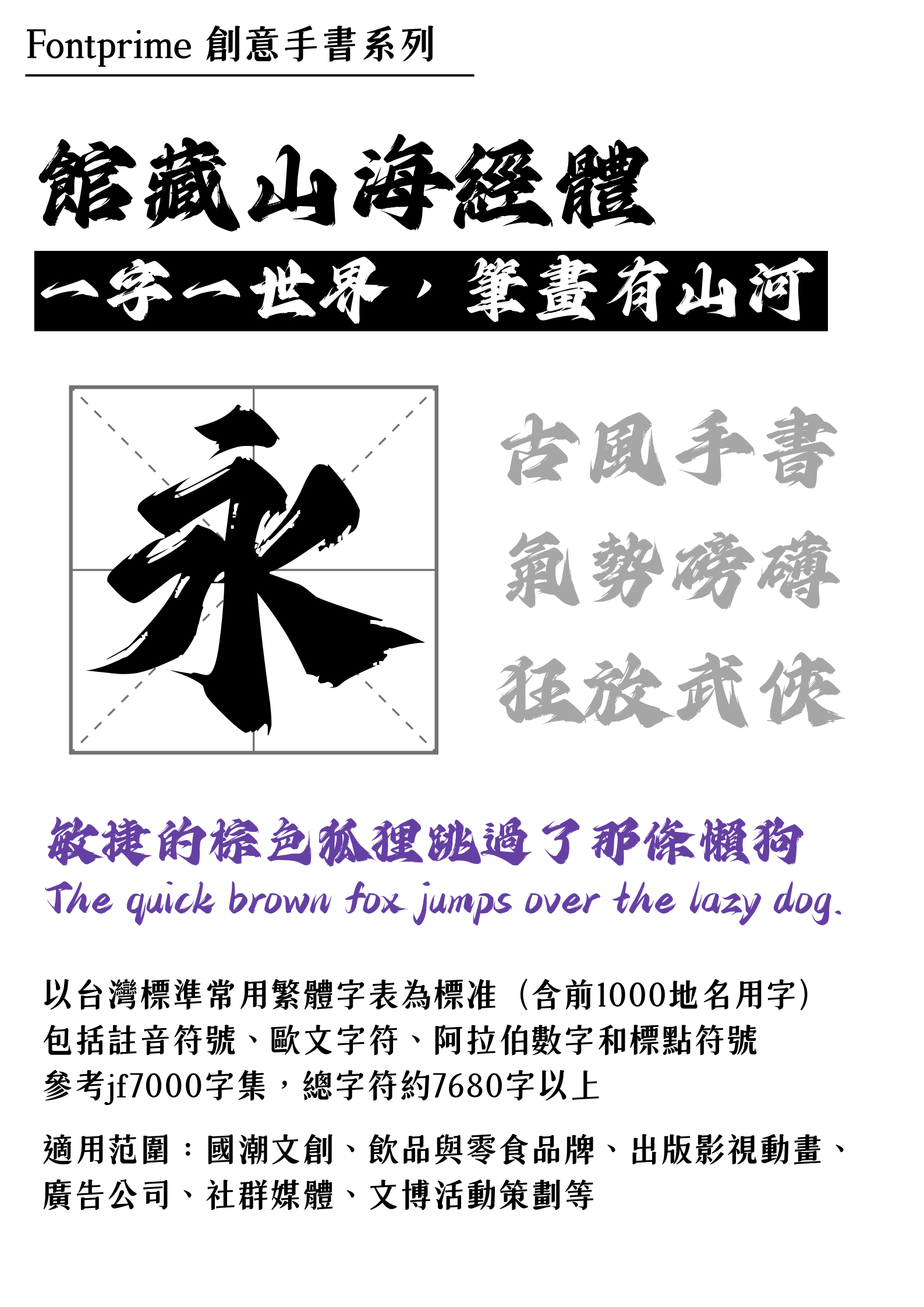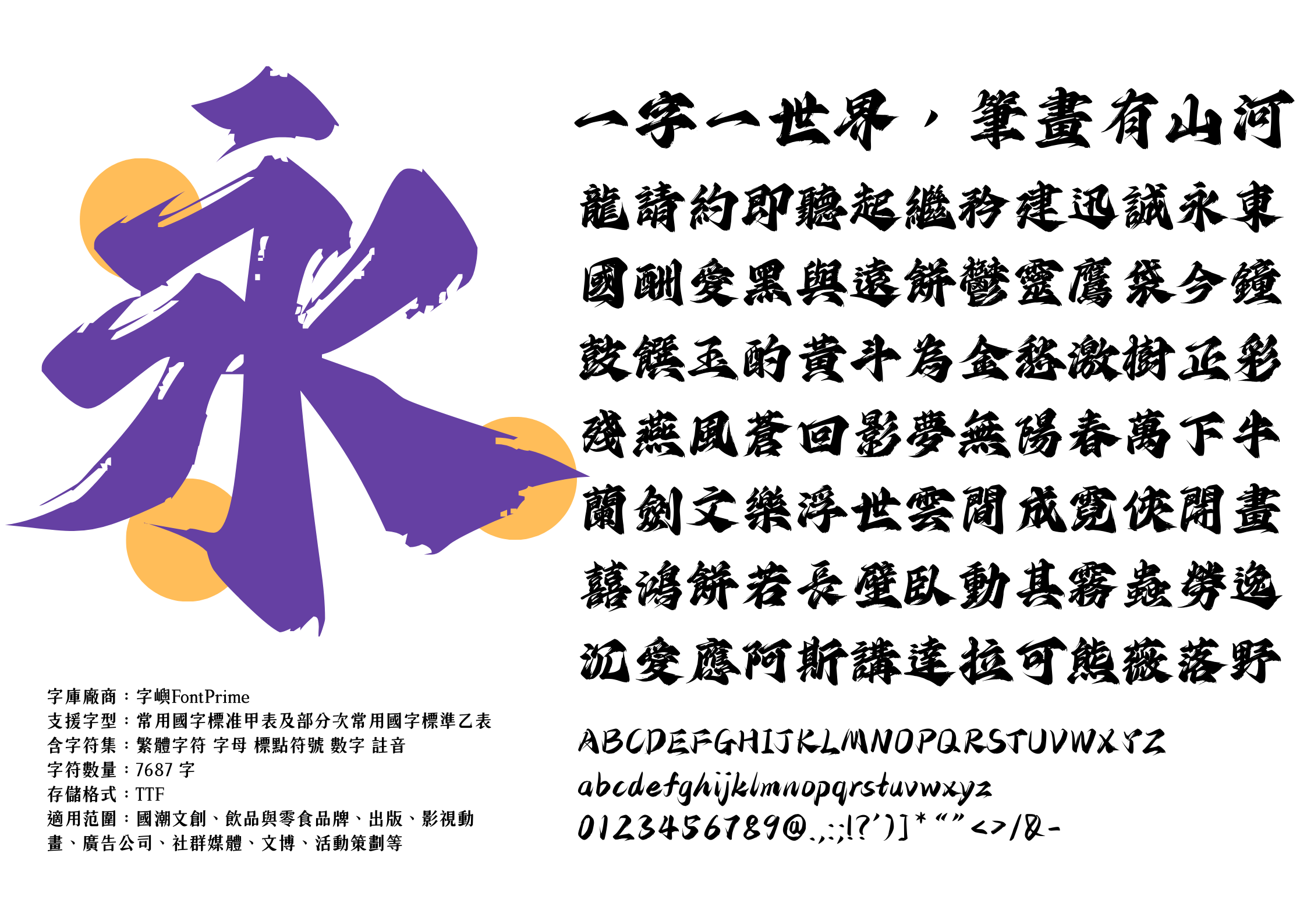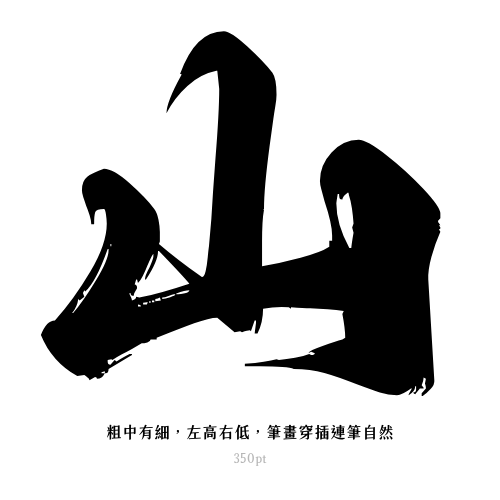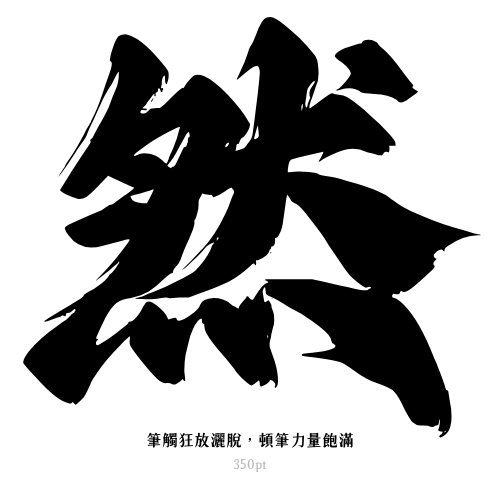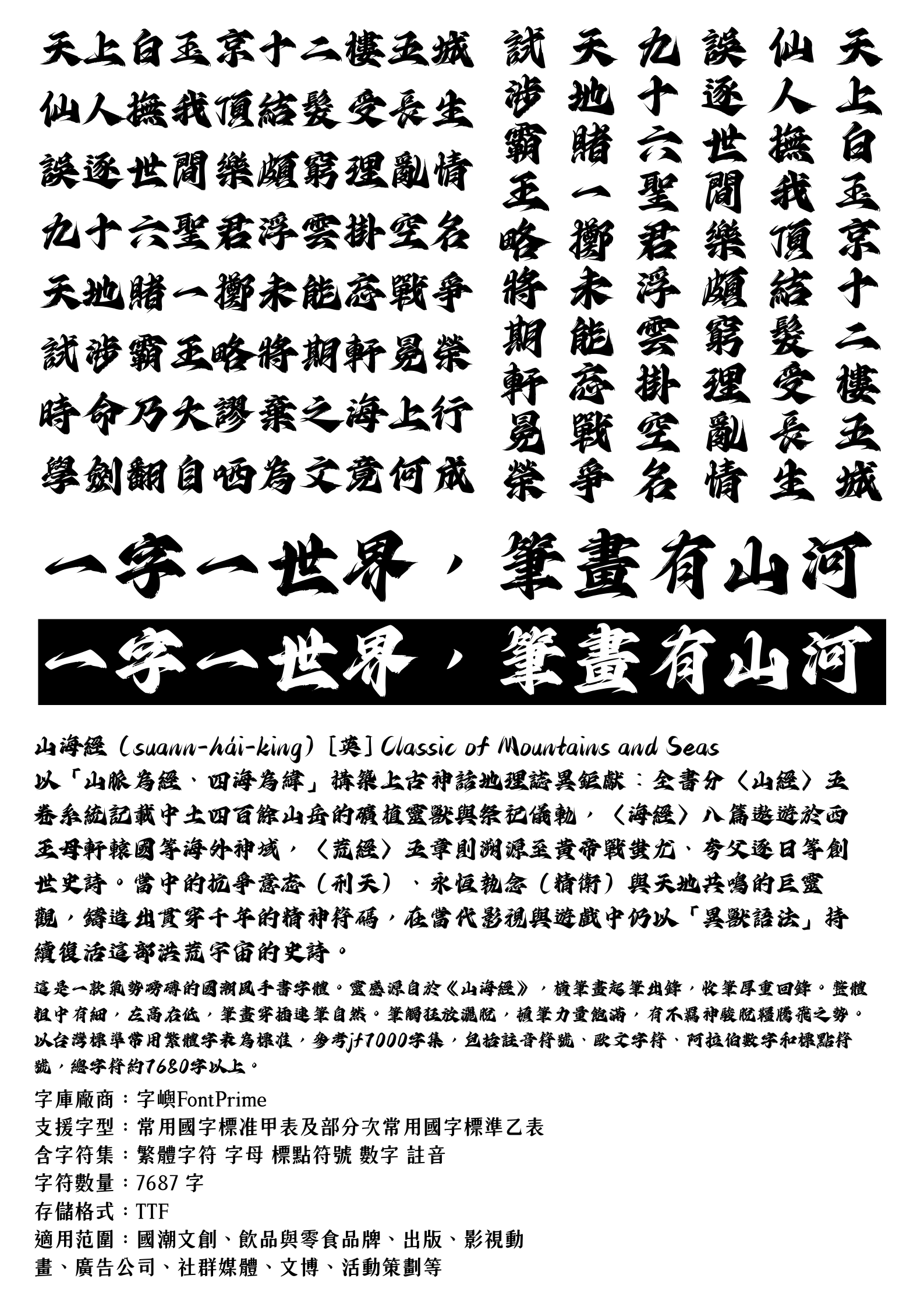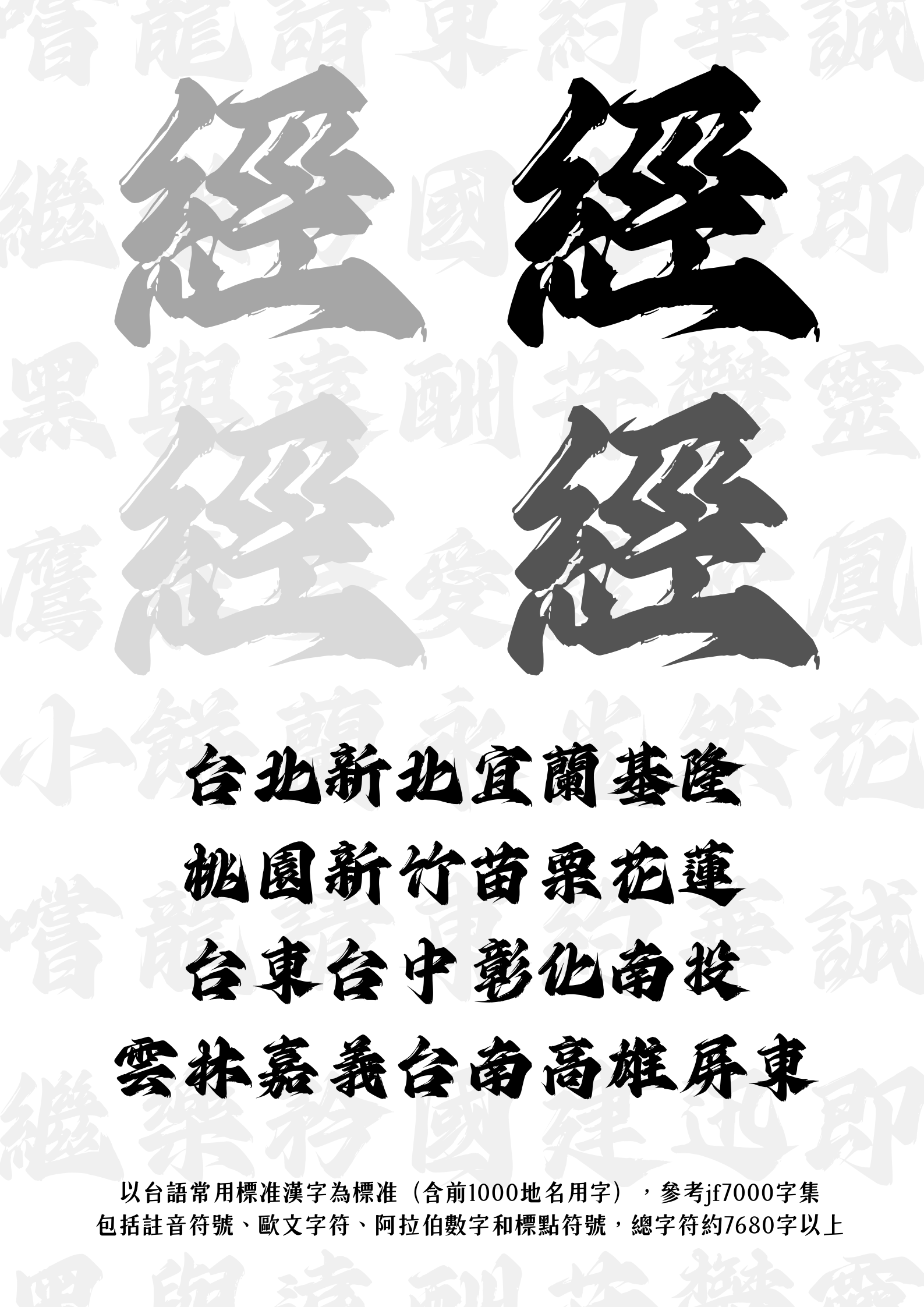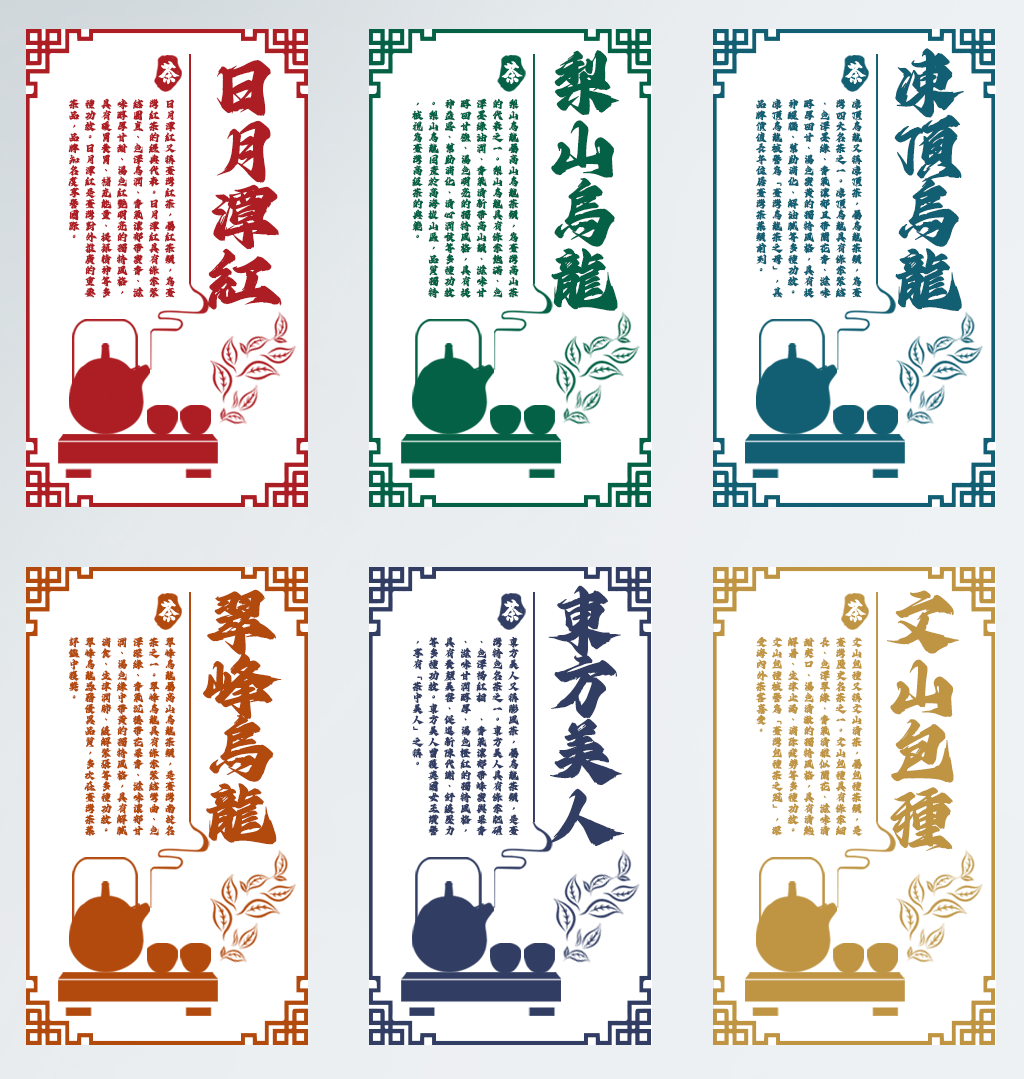
字嶼館藏山海經體
館藏山海經體 / Fontprime 簡介
- 這是一款氣勢磅礴的古風手書字體。
- 神話故事結合美術設計,靈感源自於《山海經》,比漫威早兩千年的妖怪全息圖鑑
- 「字嶼館藏山海經體」飄逸雋永、恣意灑脫,靈動自如的筆鋒讓人彷彿能夠窺見山海宇宙裡的濃墨重彩。傳統的韻味結合現代藝術的設計,讓山海經傳奇在創作者手中煥發出不同時代的獨特魅力。
這款字能為你解決什麼問題
- 填補古風繁體字缺乏的情況
市面上的古風字體以簡體或裝飾性字體為主,能兼顧繁體完整度與設計實用性的作品非常稀少。館藏山海經體正好彌補了這一缺口。 - 筆觸設計狂放灑脫,氣勢磅礴
字形設計粗中有細,左高右筆畫穿插連筆,頓筆力量飽滿。線條不僅具張力,也保持了書寫的靈動感。如果你需要表達恢宏大氣的氛圍,它是你的不二之選。 - 排版靈活,實用性強
雖然是一款古風手書字體,但在短文或段落排版中不會顯得雜亂。它在「書法筆勢」與「結構穩定」之間取得了平衡,具備良好的可讀性與靈活性。 - 提升商業品牌形象
視覺是品牌的第一印象。使用館藏山海經體,能讓品牌在市場中展現文化底蘊與差異化,迅速拉開與同類型品牌的距離,建立獨特的品牌識別。
Q5:與其他古風字體相比,它的優勢是什麼?
A5:館藏山海經體的結構更穩定,適合短文排版,筆觸更靈動狂放,能呈現氣勢磅礴的氛圍,字集完整支援繁體、注音、英數混排,解決市面上古風字體缺字多、可用性不足的問題。
創作過程與設計理念
館藏山海經體的靈感來自《山海經》這部中國最古老的神話經典,設計師在閱讀與研究過程中,試圖將文字轉化為圖像般的表現力,讓字體本身能像山川與異獸一樣,帶有故事感與張力。
設計過程中,設計師將「書法筆鋒」作為基礎,結合「山海意象」進行再創造:
- 筆觸設計:透過粗中帶細、連筆穿插的處理,模擬山巒的高低起伏與河流的奔騰律動,使字體既有力量又不失靈動。
- 結構理念:強調「穩定框架 + 自由筆勢」的結合,確保字體能應用於標題與排版,而不僅僅是裝飾。
- 文化意圖:希望在字裡行間重現《山海經》裡的想像世界,讓觀者在閱讀文字時也能感受到東方神話的浪漫與磅礴。
與市面上多數偏裝飾性的古風字體不同,館藏山海經體在設計過程中特別注重「可讀性」與「應用性」,讓它不只是一款有氛圍的字體,而是一種能真正進入品牌、出版與設計流程的工具。
我們希望這款字有無限的可能性:
- 國潮文創:如主題筆記本、刺繡掛件等周邊
- 飲品與零食品牌:可用於製作充滿奇幻感的包裝與瓶身標語
- 出版:可用於設計神話小說、古籍再版的封面與章節標題
- 影視動畫:創作奇幻劇集的開場字幕與場景題字
- 廣告公司:可用於製作兼具傳統韻味與視覺衝擊的戶外看板
- 社交媒體:可用於製作圖文貼文與短視頻標題
- 文博:可用於策劃古風主題展覽的海報與導覽冊
- 品牌:可用獨特筆觸建立國潮風視覺識別系統
- 活動策劃:可用於團隊設計主題嘉年華的門票、邀請函與舞台背景
- 手工藝者:可用於印製個性化刺繡圖案與陶瓷刻字
字嶼館藏山海經體
靈感源自於《山海經》,傳統的韻味結合現代藝術的設計,這是一款氣勢磅礴的國潮風手書字體。